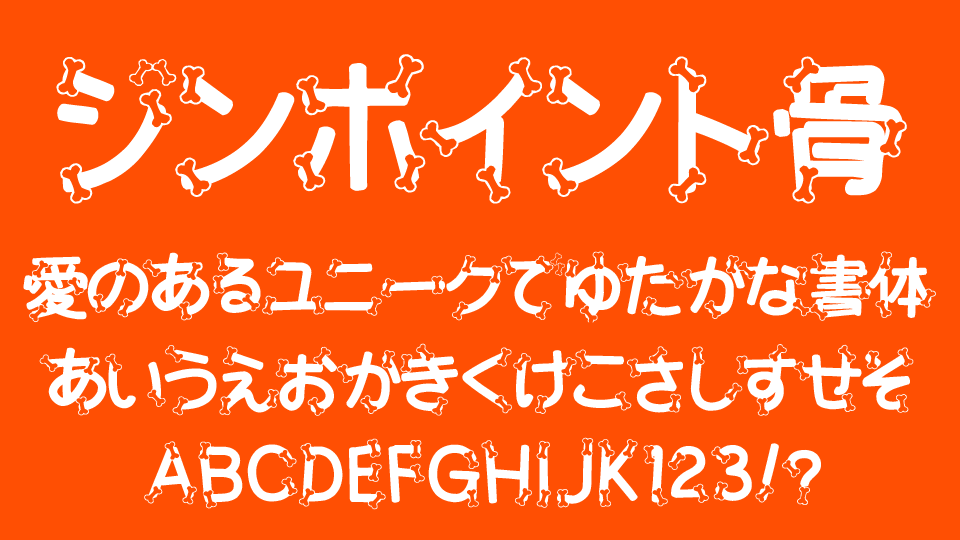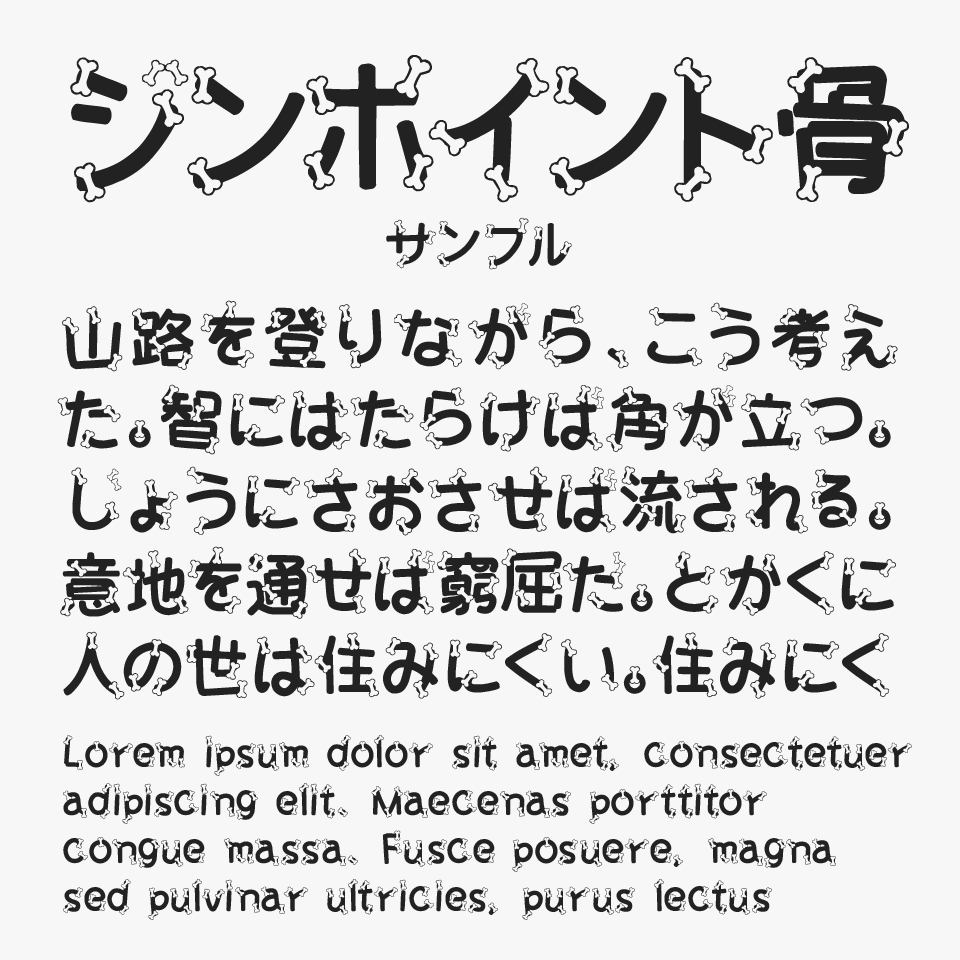
ジンポイント骨
ジンポイント骨フォントは、文字の周囲に小さな骨のモチーフを散りばめた、遊び心たっぷりのデザインフォントです。
骨をあしらっていることで、ホラーをテーマにしながらも怖さは控えめで、どこかコミカルで可愛らしい雰囲気があります。文字自体は太く読みやすいため、装飾が加わっていてもタイトルとして十分な視認性があります。
ハロウィンイベント、ホラー作品、モンスターやゾンビをテーマにしたデザイン、ゲーム、子ども向けイベント、POPなどにぴったりです。少し不気味で楽しい世界観を作りたいときにぴったりなフォントです。